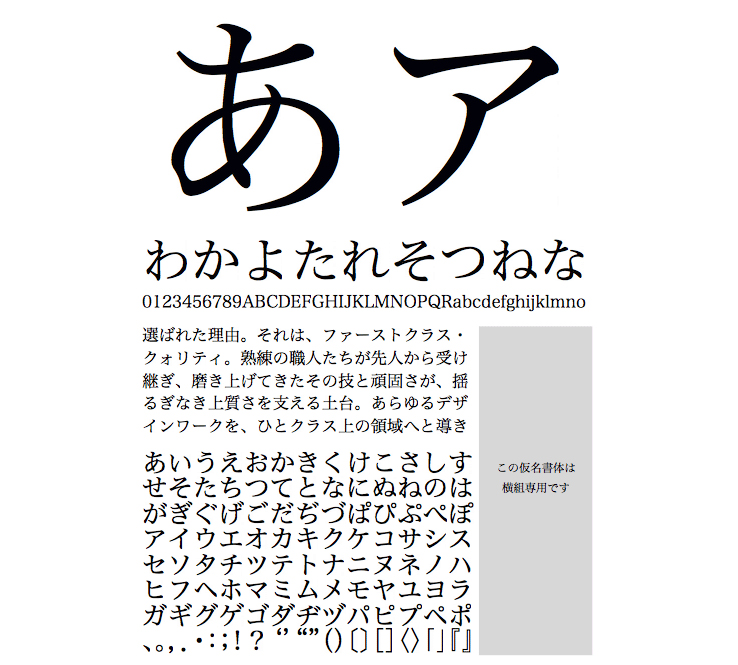
仮名・英数字グリフのみ収容
※本商品は仮名書体です。ギャラリーの見本に含まれる漢字はヒラギノ明朝を使用しています。
【ヒラギノ明朝横仮名】「ヒラギノ明朝」のデザインに合わせた横組み用の仮名書体です。横組ベタ送りの組版でも字間に粗密が少なく、美しくラインが揃うように、組まれた版面の濃淡が均一になるようにデザインしています。なお、「ヒラギノ明朝 Pro / ProN W3・W6」には、この横組み用かなが入っておりOpenType機能から呼び出すことが可能です。